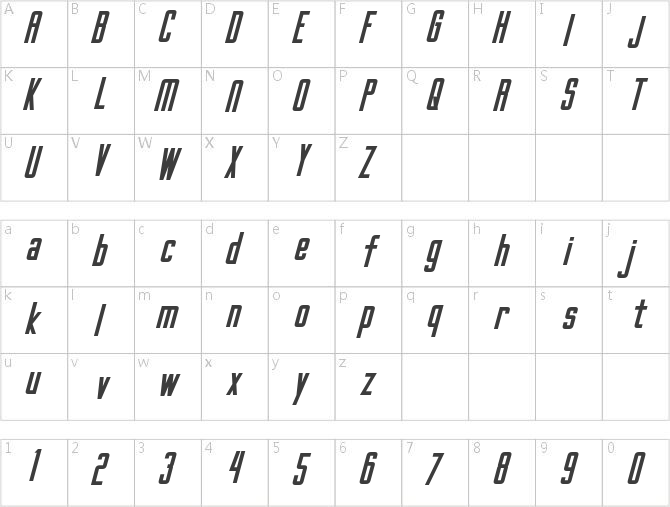
Gotham Nights Bold Italic
Gotham Nights Bold Italic介紹
Gotham Nights Bold Italic字體字庫是一款讓人賞心悅目、百看不厭的英文字體,適合各類廣告和產品包裝設計應用,字體大小0.06MB,格式為ttf字體,上傳用戶是13226568769,作者/版權方為未知